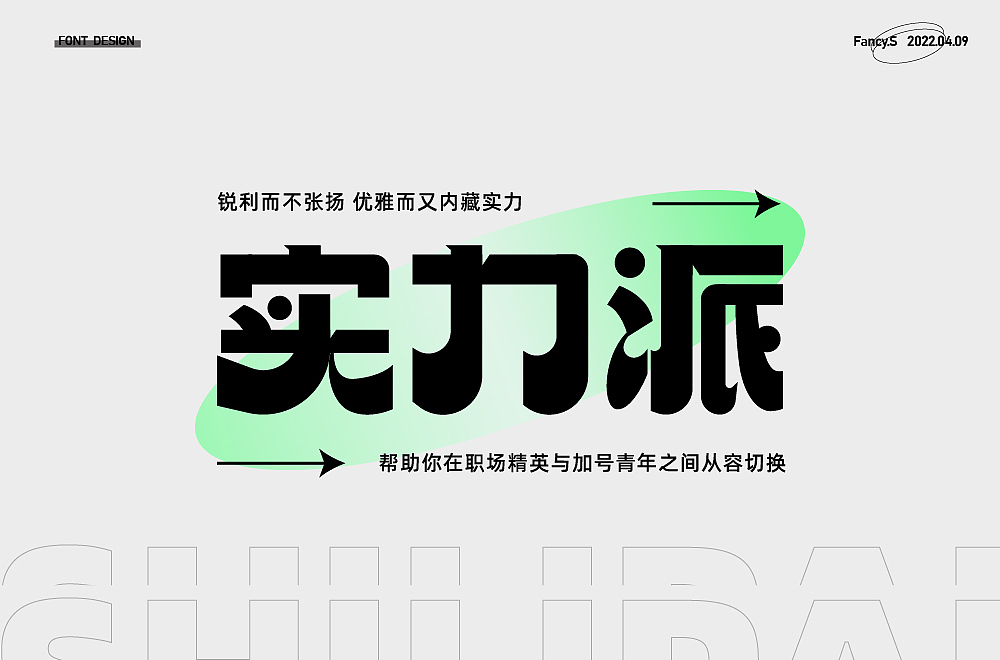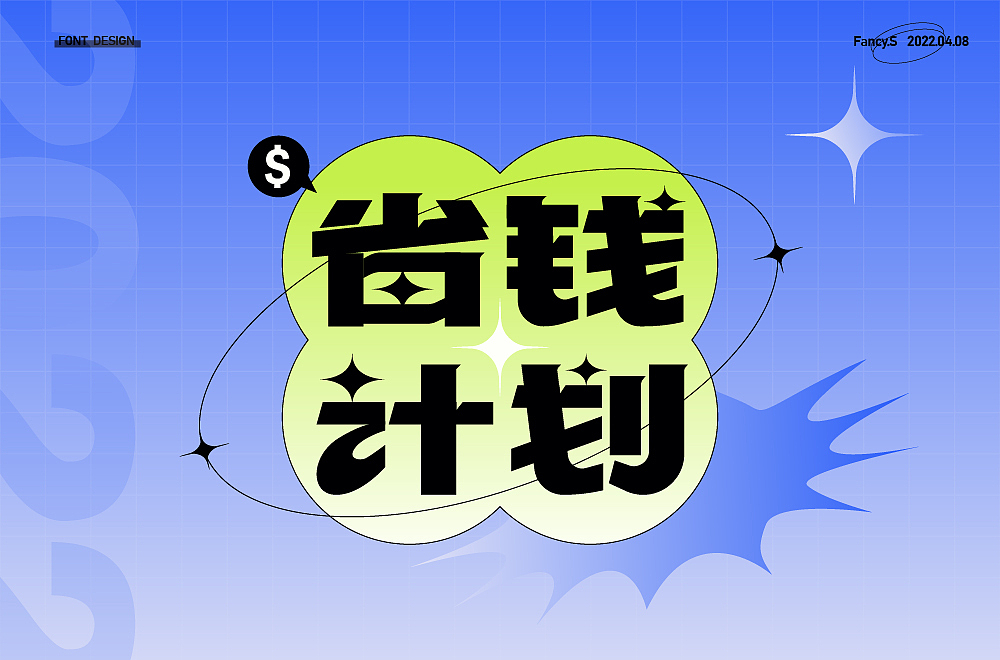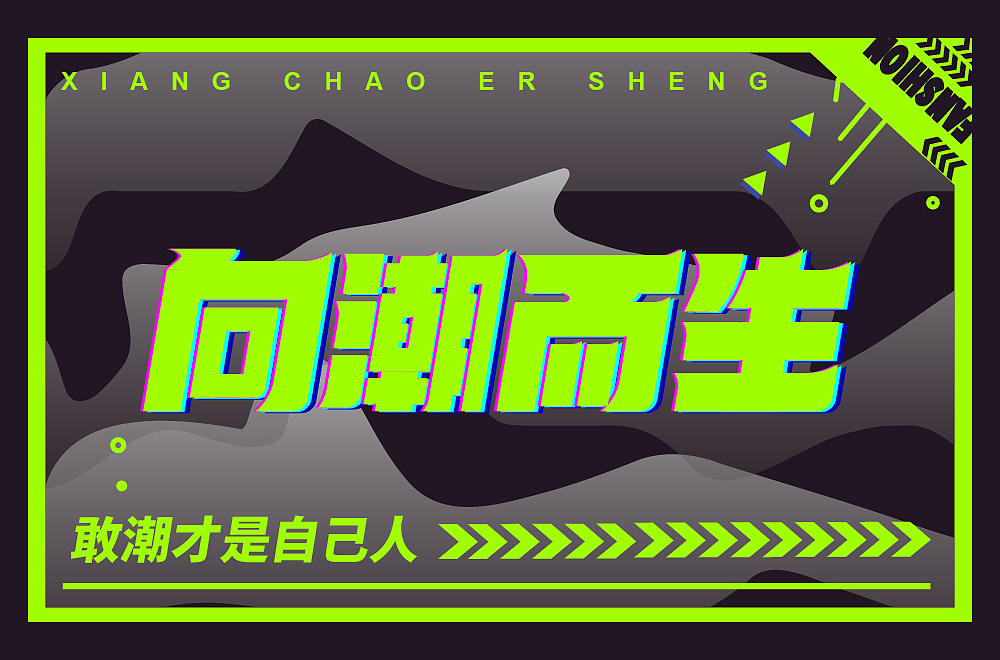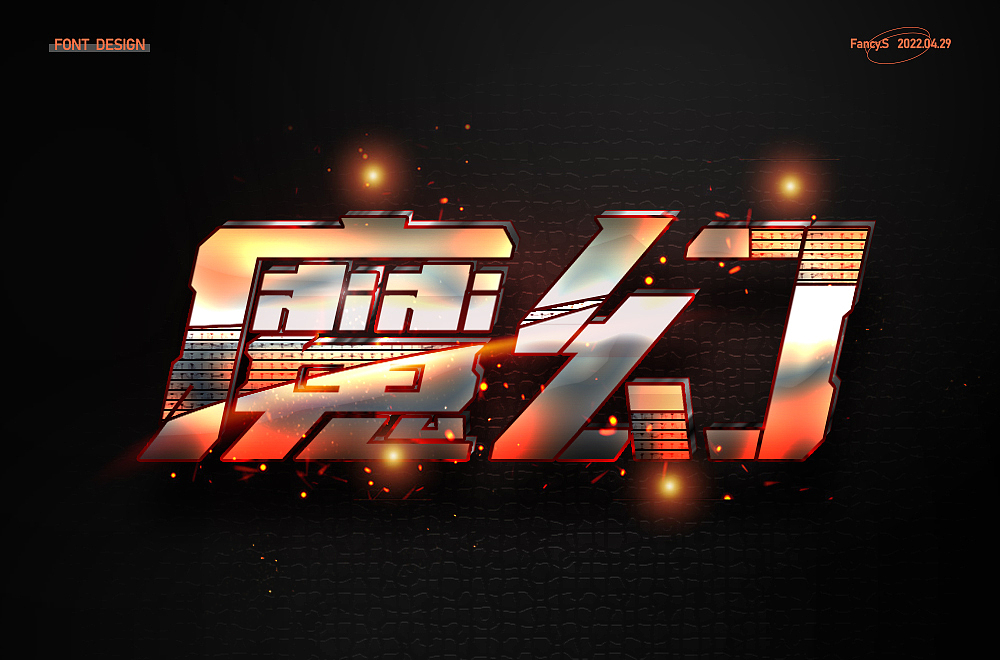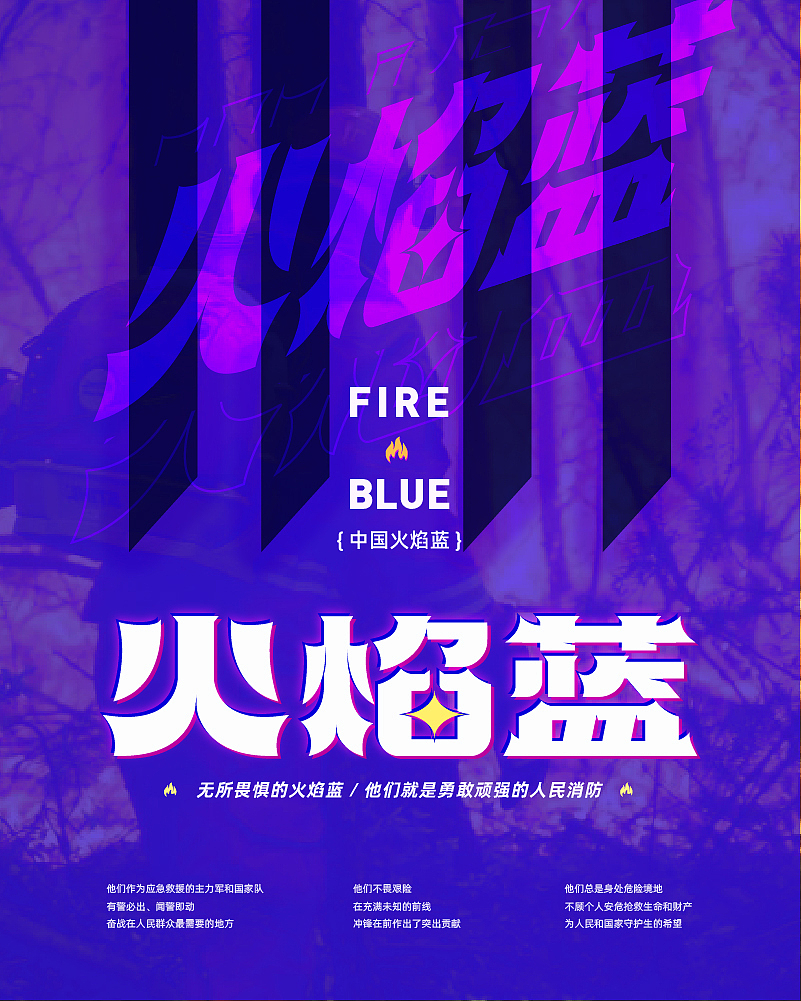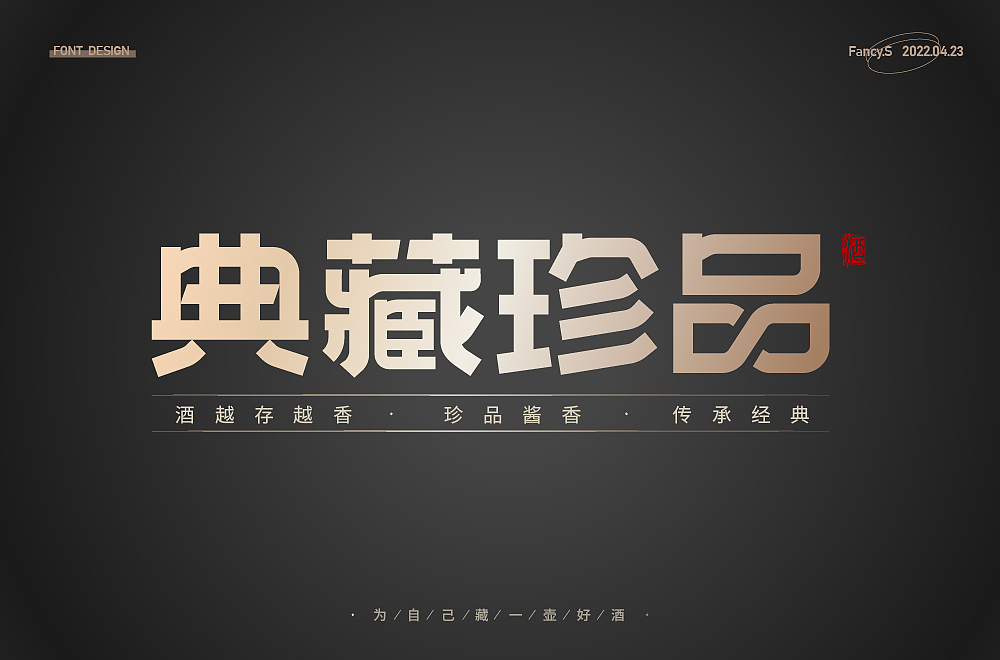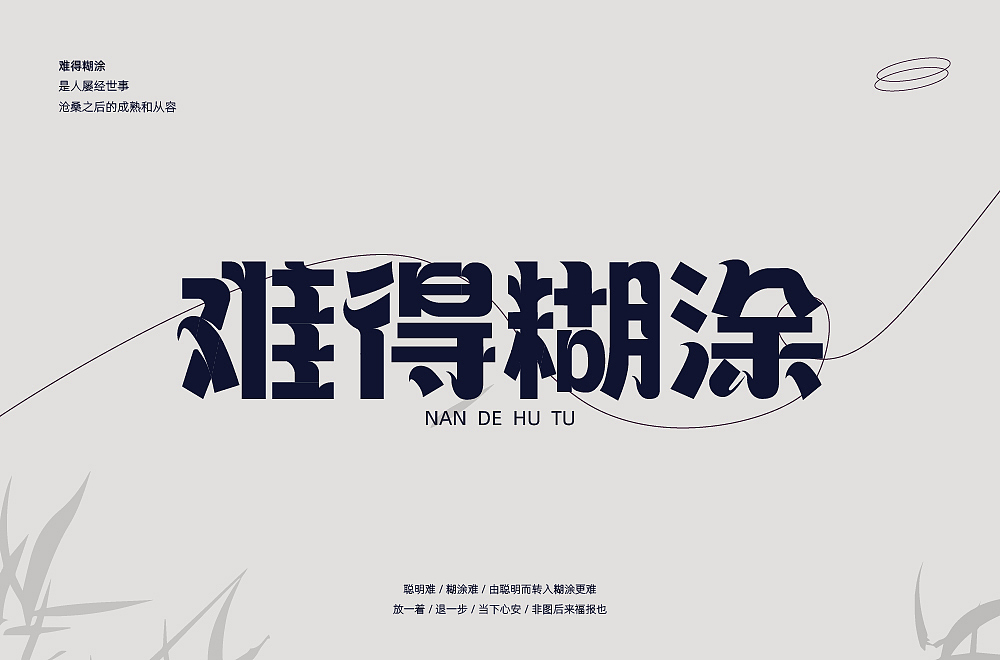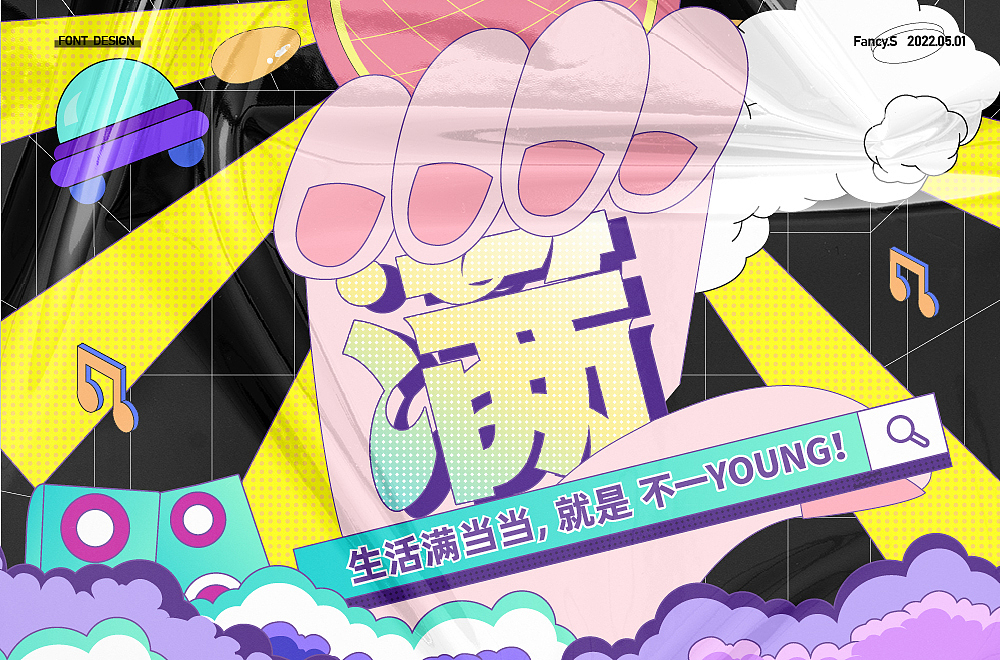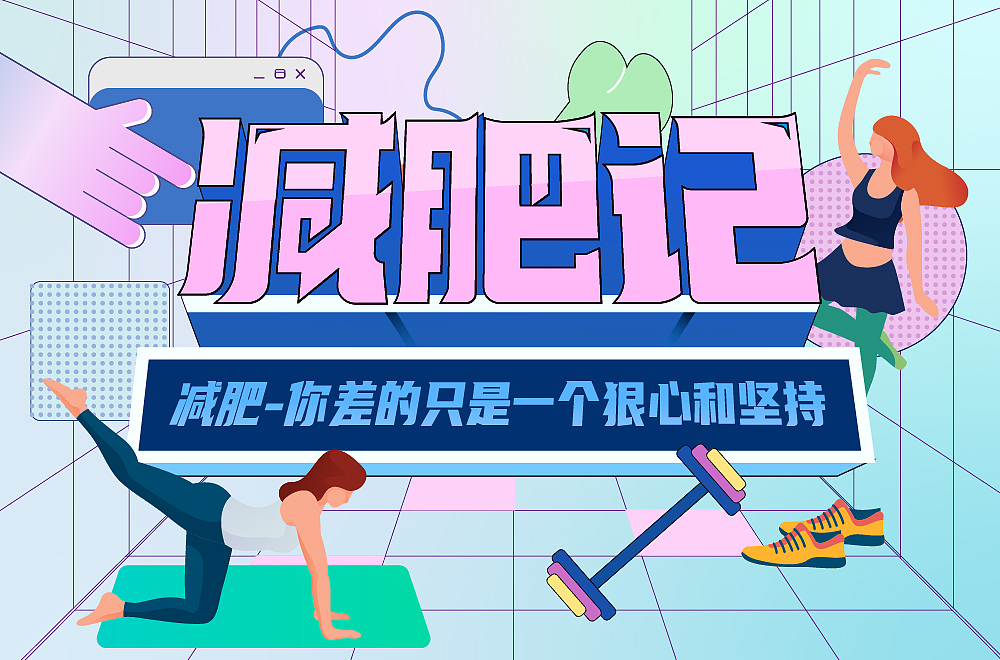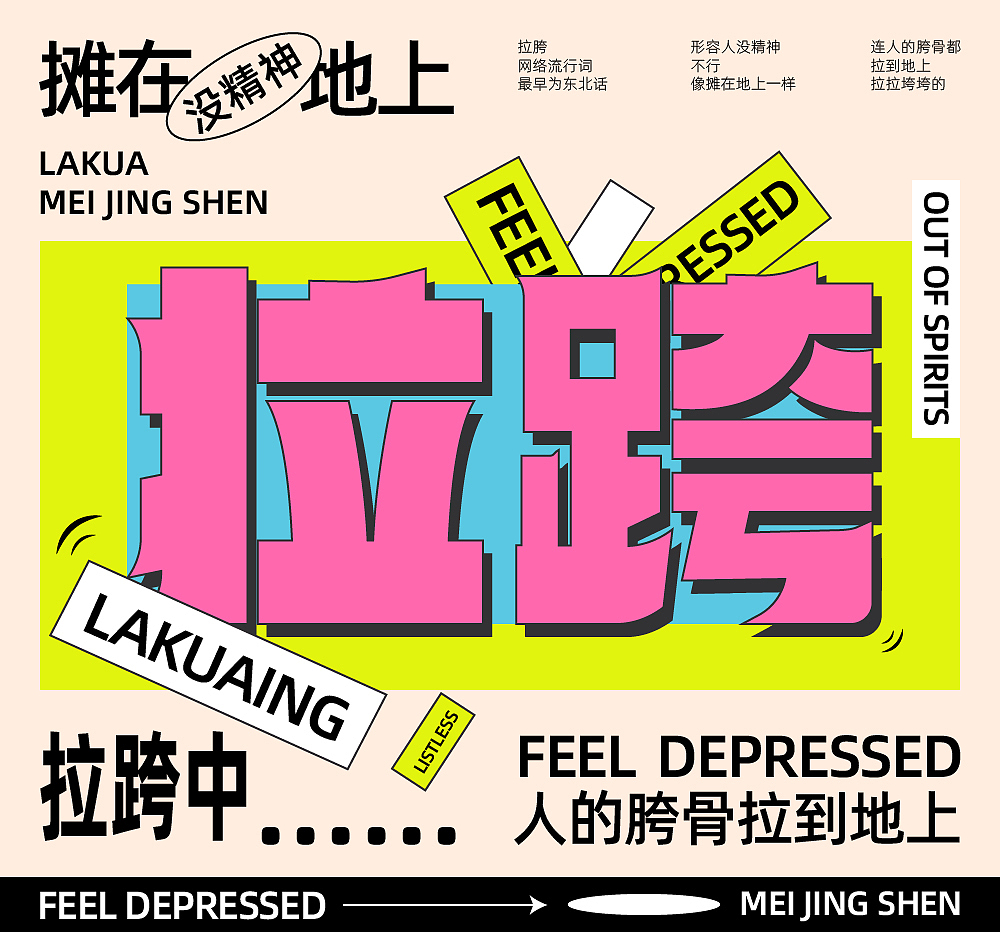
字体练习合集
又一次50天的每日一字练习结束了,
大家互相分享,互相给予意见,收获特别多~
同时也发现自己的很多问题,有时候也会很纠结,
不仅纠结该怎么做字,纠结用什么风格,用什么样的排版,用什么样的设计形式,
同时也在纠结自己坚持的意义在哪里。
为什么大家都说要”坚持“,”贵在坚持“,其实坚持做一件事情并不难,
难在自己在一直做这件事过程的思维变化,
人们的思想是比较难以控制的,
会受外界更多的干扰,
所以从一而终,坚持就会变得难了~
整理这一波练习的时候,突然发现矩形字偏多,
而且营造氛围版式也比较多,
就简单筛选了一下,做了整理归类~~
总览集合